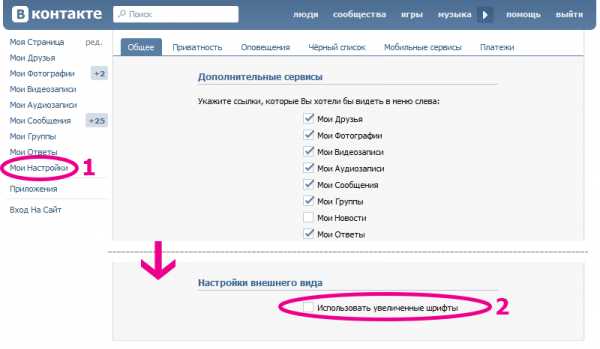
В связи с тем, что на сайте ВКонтакте шрифт достаточно мелкий, у многих людей, которые испытывают проблемы со зрением, быстро устают глаза. Следовательно, возникает потребность уменьшении или увеличении масштаба. В этой статье мы расскажем о всех возможностях для изменения шрифтов, которые доступны в рамках сайта ВК.
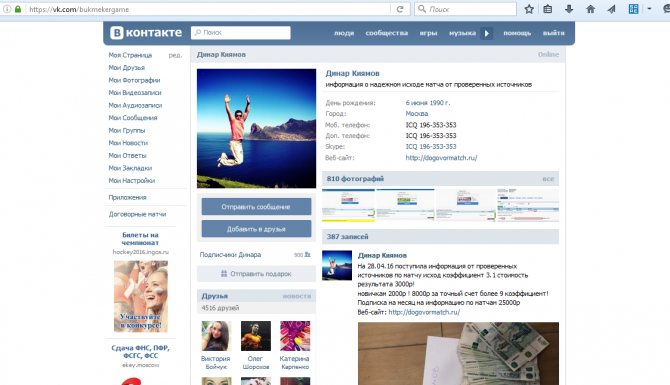
Как сделать шрифт меньше в ВК на айфоне?
Изменение размера шрифта
- Выберите «Настройки» > «Экран и яркость» и установите флажок «Размер текста».
- Перетащите ползунок, чтобы выбрать требуемый размер шрифта.
Редактор Stylish
Для браузера Google Chrome есть дополнение под названием „Stylish“. Используя данное дополнение, вы можете бесплатно изменить дизайн ВК, размер букв, а также выполнить с ними другие действия. Здесь вы можете подобрать любое оформление, а также создать его самостоятельно. Рекомендуем данный редактор тем пользователям, которые стремятся подчеркнуть свою индивидуальность, сделать свою страницу более привлекательной, заметной для друзей и подписчиков. Скачать приложение можно в магазине дополнений Google Chrome. Процесс установки выполняется в автоматическом режиме.
Дизайн: один для всех устройств
Изменение, которое заметят все, — это свежее оформление vk.com. Иконки стали ярче и лаконичнее, а шапка сайта сменила синий цвет на белый.
Кажется, что вы это уже где-то видели? Всё верно — в мобильной версии и мобильном приложении VK. Делаем так, чтобы дизайн ВКонтакте был похожим на всех устройствах, а ещё не отвлекал громоздкими элементами от общения и увлекательного контента.
Увеличение шрифта
Способ №1:
- Зайдите в свою учетную запись VKontakte, затем перейдите в раздел „Настройки“.
- Пролистайте немного вниз, в „Настройках внешнего вида“ поставьте отметку возле „Использовать увеличенные шрифты“. Для уменьшения сделайте наоборот.
Способ №2:
- Перейдите в настройки веб-обозревателя, который используете для входа на сайт.
- В разделе „Масштаб страниц“ увеличьте размер текста на странице до того процента, который подходит именно вам.
Отрегулировать масштаб страницы можно с помощью клавиатуры и мышки. Увеличение размера текста – зажмите клавишу „CTRL“ и „+“ или нажмите „CTRL“ и прокрутите колесико мыши вверх.
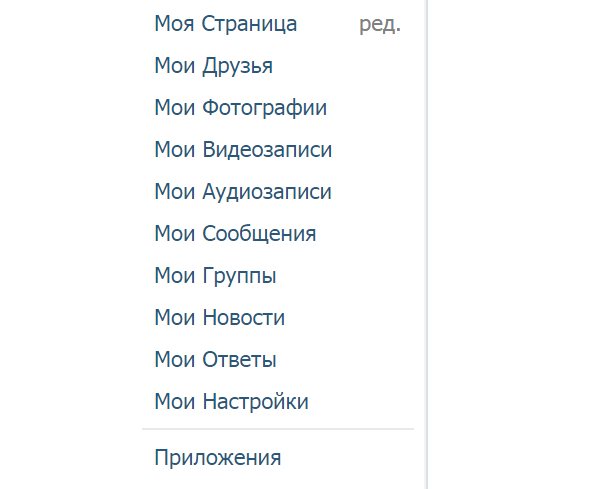
Какой шрифт используется Вконтакте для надписей на картинках
Сегодня я слегка озадачился поиском подходящего кириллического шрифта, который бы было можно использовать в фотошопе для нанесения красивого текста на картинки.
Уверен, многие знают, что большинство шрифтов, которые установлены на компьютере по умолчанию или те, что были отдельно занесены в коллекцию не поддерживают русские символы (буквы).
В общем, я решил найти какой-нибудь русский шрифт для фотошопа, и почему-то сразу же вспомнил про красивые надписи, которые используются на большинстве картинок в социальной сети «Вконтакте».
Пример шрифта
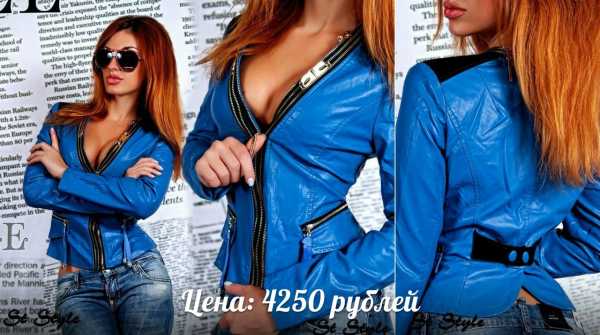
На этой картинке один из примеров шрифта, который я хотел найти и добавить в свой Photoshop CS6, но вот не задача – найти его оказалось не так уж и просто.
Сначала я решил воспользоваться поисковой системой Яндекс, что бы найти хоть какие-то зацепки, но перебрав все возможные варианты для запросов, я так ничего и не нашёл.
- Какой шрифт используется ВКонтакте для надписей на картинках?
- Какой шрифт использован Вконтакте
- Русский шрифт для картинок как в ВК
- Распознать русский шрифт по картинке
- Русский шрифт для картинок
- Русский шрифт для фотошопа
И лишь немного позже, прибегнув к ответам от Mail.ru в одном из комментариев я нашёл что-то похожее. Оказалось для надписей на картинках ВКонтакте чаще всего используют шрифт под названием Lobster (Лобстер).
Lobster — шрифт для надписей на картинках Вконтакте
Прежде чем я нашёл то, что искал, помимо всего прочего мне пришлось потратить некоторое время на так называемые сервисы по распознаванию шрифтов на картинках, но результаты оказались неверными или и вовсе отсутствовали.
Предполагаю что вопросом, какой шрифт используется в VK.com для надписей на картинках, интересуется немало людей, поэтому я решил сделать эту заметку и сохранить шрифт Lobster у себя на «Яндекс Диске» что бы его было можно скачать при необходимости.
Если очень хочется, можешь нажать клавишу Caps Lock и писать ЗАГЛАВНЫМИ БУКВАМИ. Но тогда люди будут считать, что у тебя истерика, и читать твои послания на самом деле никто не станет. Может быть, ты просто хочешь выделиться, стать заметнее, чтобы на тебя обратили внимание? Тогда попробуй надеть красную кофточку. Удачи тебе!